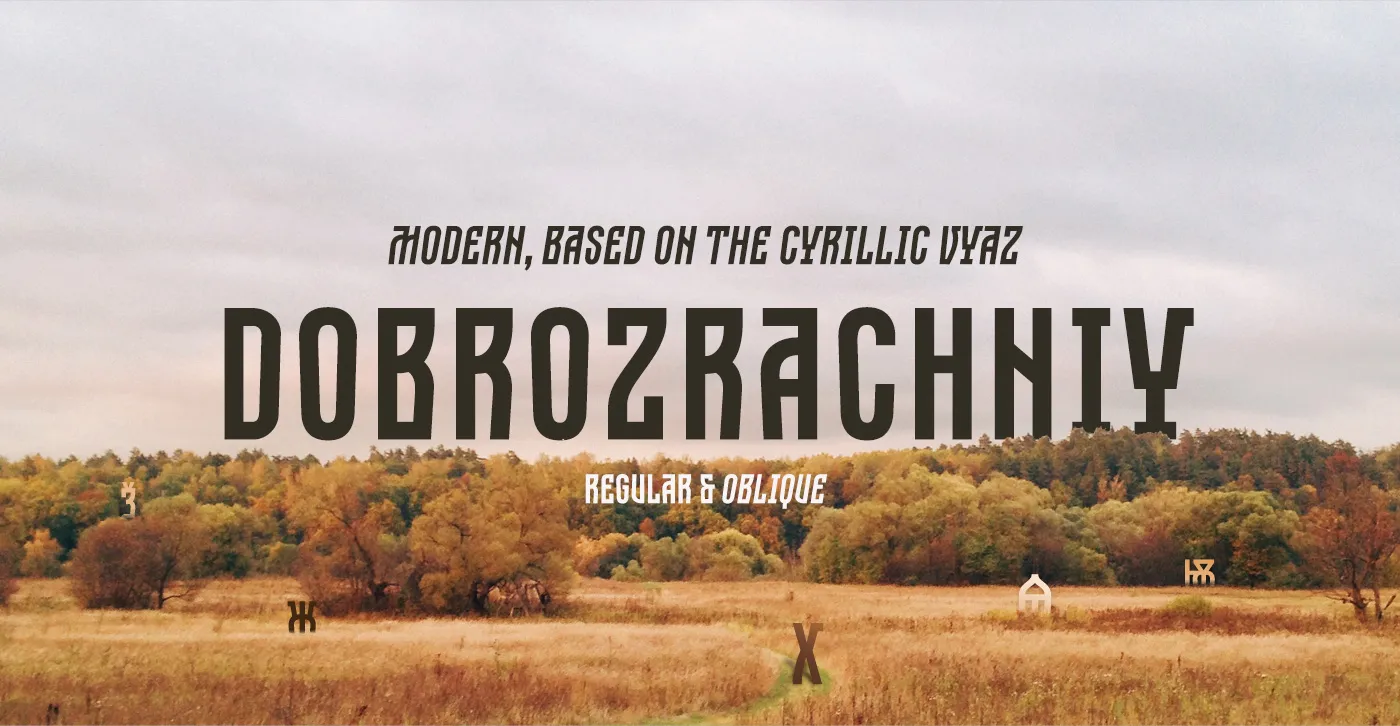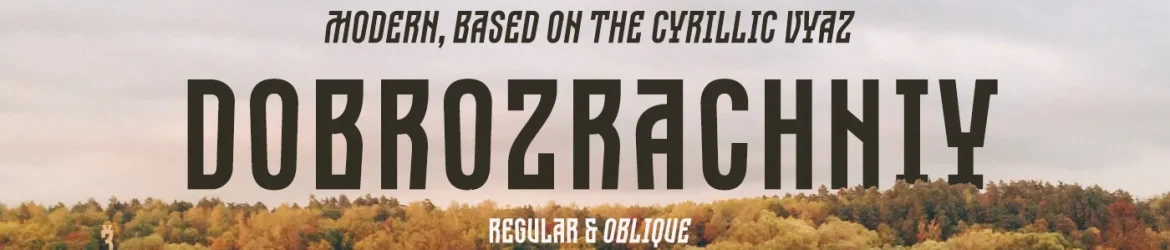
A Dobrozrachniy Typeface é uma fonte display desenvolvida pelos russofonts e traz uma experiência única para os designers. Embora sua origem esteja na pre-Petrina escrita cirílica, a Dobrozrachniy traz elementos estilizados da Art Nouveau, resultando em um grotesco acidental com proporções estreitas e baixa contraste. Esta fonte é uma peça perfeita para aplicações que requerem destaque e impacto visual, como headlines, logotipos e ilustrações, bem como para gráficos de artefatos ou embalagens. Com duas opções de peso: normal e obliquo, ela oferece flexibilidade para adaptar a aparência da fonte ao seu projeto específico. É uma ótima escolha para aqueles que buscam um design único, com personalidade e estilo, sem comprometer o texto.